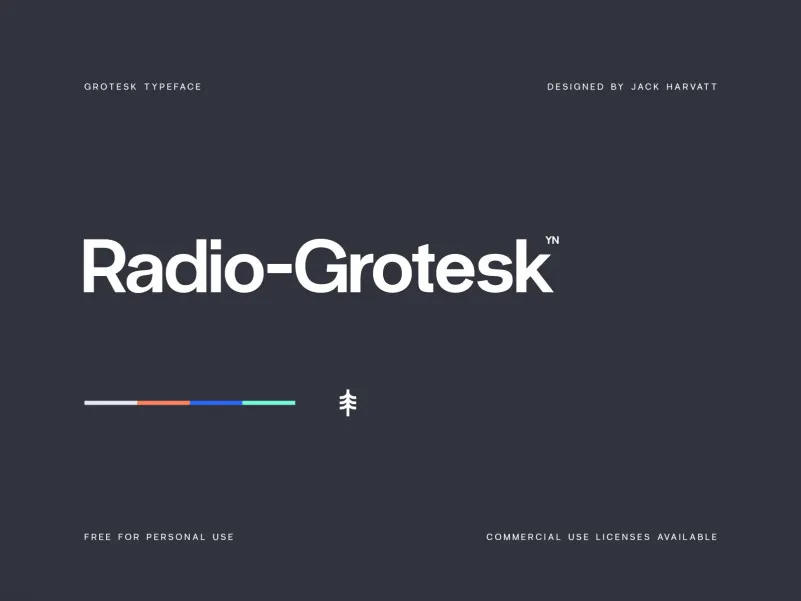
A Radio Grotesk Font Family é uma elegante escolha para quem busca beleza e legibilidade na tipografia. Inspirada no estilo Grotesque sans-serif, essa família de fontes incorpora um toque de personalidade nos caracteres, sem deixar de lado a clara leitura que é essencial em qualquer projeto gráfico. Suas minúsculas sofisticadas e maiúsculas bem estabelecidas dão ao conjunto um caráter contemporâneo dentro do tradicional estilo tipográfico. Desenvolvida para uma vasta gama de aplicações, desde a web até o design editorial, esta família de fontes é perfeitamente adaptável para qualquer projeto. Com três pesos de negrito que permitem uma adaptação fácil a diferentes contextos e estilos, Radio Grotesk pode ser usado tanto em textos profissionais quanto em elementos de design gráfico. Para os usos mais visuais, como sinalização ou arquitetura, essa família de fontes é uma ótima escolha. O conjunto de 340 gílipes (letras) em cada uma das três variantes linguísticas do America e grande parte da Europa garantem que a Radio Grotesk seja uma opção versátil para qualquer projeto. Introduzindo um toque moderno em um estilo tipográfico clássico, Radio Grotesk Family é uma excelente adição à coleção de fontes. Para designers digitais e gráficos, esta família não só oferece beleza, mas também alegria aos projetos que usam suas linhas limpas e modernas.